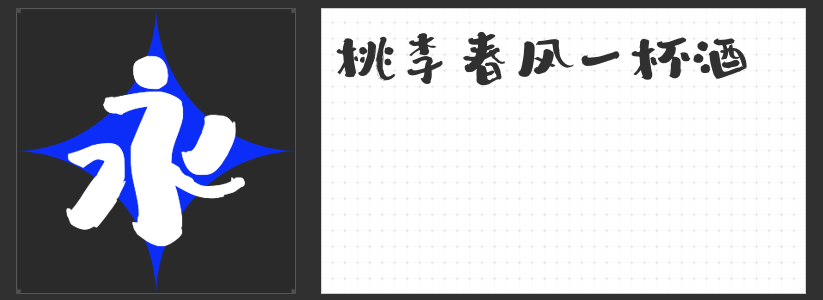
四款毛笔字体美学典范:以笔锋挥洒东方气韵
毛笔字体作为中华文化的视觉符号,承载着千年书道精髓。在当代设计中,四款各具神韵的毛笔字体突破传统框架,以创新笔法重构东方美学,为创作注入苍劲、灵动、古拙与磅礴的多元气质。
一、造字侠伏魔简繁 传神
这款字体以浓墨堆叠出雕塑般的立体感,粗细对比犹如刀劈斧凿,在方正结体中暗藏收放自如的张力。夸张的勾挑笔画如金石崩裂,捺画收尾的顿挫似战鼓擂动,将书法中的"骨法用笔"转化为极具压迫感的视觉语言。其运笔轨迹中保留的飞白肌理,更让每个字符都蕴含着蓄势待发的能量,堪称力量美学的终极诠释。
二、造字侠醉春风简繁 苍劲
与伏魔体的刚猛形成戏剧性反差,这款字体以圆润点画演绎率真天性。看似随性的笔画走势中,实则暗藏精妙控制——粗细过渡如春风拂柳,字形结构在周正与松弛间达成微妙平衡。灵动的连笔设计打破传统毛笔字的程式化表达,让每个字符都成为跃动的生命体,特别适合需要传递轻盈感与自然意趣的创作场景。
三、万人字造踏歌行体
此体以方整结体为基底,通过斑驳笔触复刻岁月沉淀的质感。劲健的笔力中蕴含蓄势待发的动态,圆润转折处又见从容气度。古法用笔的基因与现代设计语言在此交融,既保留碑刻的庄严感,又通过笔画间的呼吸感让传统书法焕发当代生机,堪称连接古今的视觉桥梁。
四、造字侠磅礴简繁
这款字体将书法节奏感推向极致——运笔如乐章起伏,转折处方圆相生,飞白笔触似未尽余韵。粗细对比强烈的笔画如交响乐中的强弱拍,在视觉上形成自然引导线。其丰富多变的中正结构,既可独立成篇,亦能与不同风格元素和谐共舞,为创作提供无限可能的节奏把控。
这四款毛笔字体以笔为刃,在传统与现代之间劈开新径。它们突破程式化的表达范式,让毛笔字不再是简单的文化符号,而成为具有独立审美价值的艺术语言,为当代设计注入东方美学的深层基因。